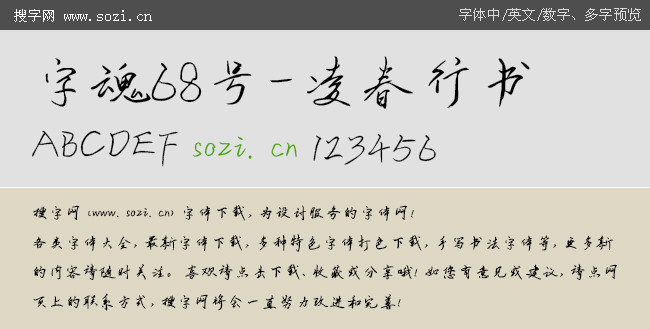
字魂68號(hào)-凌春行書
搜字網(wǎng)提供一款字魂68號(hào)-凌春行書中文字體下載,該字體是一款硬筆手寫字體,該字體包含6763個(gè)中文、字母、 符號(hào)和數(shù)字,具有帥氣、豪放、中國風(fēng)、古典 的風(fēng)格,可以滿足您設(shè)計(jì)上的各種需求,該字體主要用于新媒體、活動(dòng)、美食餐飲、企業(yè)店鋪、廣告、影視傳媒 等場景。